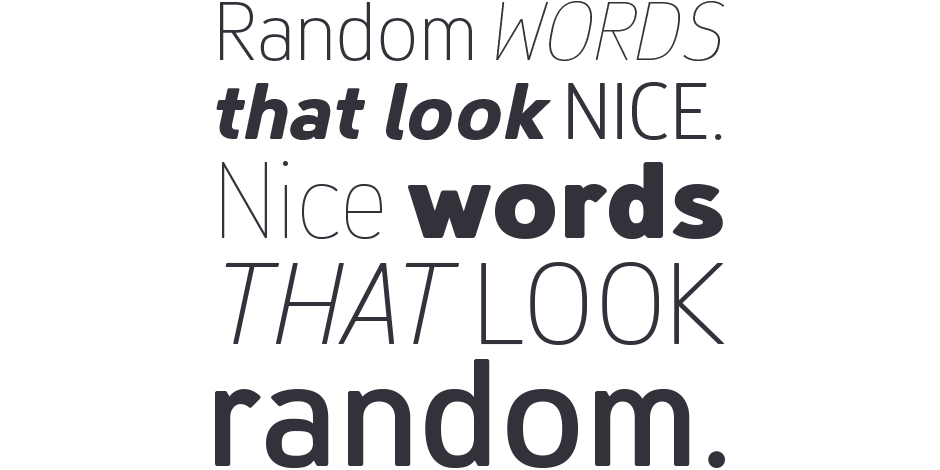
Finador est une famille de caractères sans empattement modernes et doux. Le style fonctionnel d'un sans-serif a été adouci par des ouvertures et des coins arrondis. Finador est ainsi fonctionnel et convivial.
Famille
Finador est une famille de caractères modernes et doux sans empattement avec un total de 16 graisses, de fine à lourde, et des italiques assorties.
- La version par défaut présente des ouvertures ouvertes et modernes. Le jeu stylistique 2 comprend le jeu de lettres avec des ouvertures fermées, classiques. Un look légèrement différent. C'est comme si vous aviez un deuxième police.
- La famille Finador comprend de nombreuses caractéristiques OpenType telles que les petites capitales, les ligatures, les fractions, les alternances et bien d'autres encore.
Racines
Après le Bourget, premier caractère de Julien Fincker - un display police à une graisse - le Finador est son premier caractère à plusieurs graisses. Les premières esquisses avaient déjà été dessinées avant et parallèlement à Bourget, et ont été rapidement abandonnées. Avec le processus d'apprentissage de la théorie et de la pratique, il y avait tellement d'erreurs dans la forme et la fabrication que Julien a décidé de redessiner tout l'alphabet. Au cours du processus de conception, il a beaucoup appris sur les fonctions OpenType qui ont permis d'augmenter le jeu de caractères à plus de 900 caractères. Le Finador a donc rapidement dépassé son rôle de police de caractères d'apprentissage pour devenir une famille de caractères polyvalente. Il est devenu universellement applicable - un véritable cheval de bataille.
Lisibilité
Les graisses les plus fines et les plus épaisses conviennent particulièrement aux titres, tandis que les graisses moyennes peuvent être utilisées pour les défis typographiques et le corps de texte. Une grande hauteur de x, un faible contraste et des ouvertures ouvertes assurent un haut niveau de lisibilité typographique.